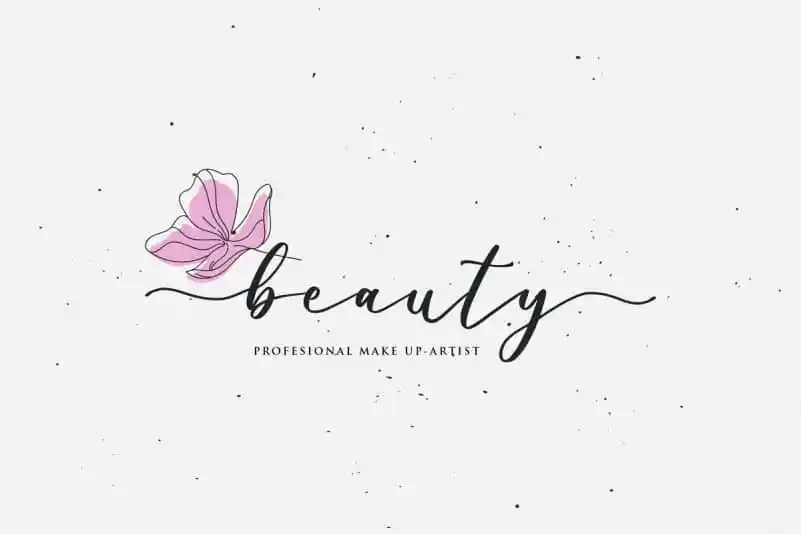
Belagia Calligraphy Font – Download Grátis
Seja bem-vindo a todos os amantes de fontes! Estamos muito felizes em apresentar uma nova oferta chamada Belagia Font. É uma linda fonte de calligrafia moderna e elegante, cuidadosamente criada para atender aos mais variados estilos de design. Belagia é uma fonte de script perfeitamente balanceada entre feminino e sofisticado. Ela traz um toque romântico que combina a elegância eterna com o autêntico estilo da calligrafia, resultando em letras com espalhafatosos finais e início. Este é um conjunto perfeito de beleza e charme para uso em diversos cenários como casamentos, food blogs, lojas online ou qualquer empresa que busca dar uma aparência sofisticada e delicada a seu trabalho. Belagia será um acréscimo incrível à sua biblioteca de fontes, tornando seus projetos ainda mais irresistíveis e únicos.